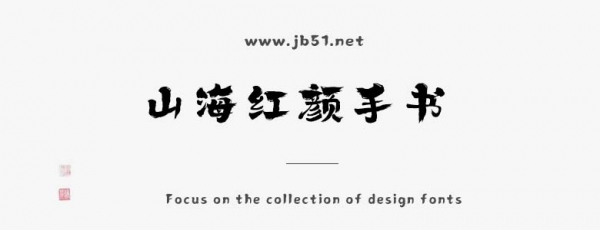
山海紅顏手書(shū)W是由山海字庫(kù)出品的字體,這款字體筆觸略粗,書(shū)寫(xiě)隨性灑脫,具有很好的視覺(jué)感,適合應(yīng)用于藝術(shù)設(shè)計(jì)、平面宣傳設(shè)計(jì)、網(wǎng)頁(yè)設(shè)計(jì),書(shū)法字帖等領(lǐng)域,需要的朋友可以前來(lái)本站下載。